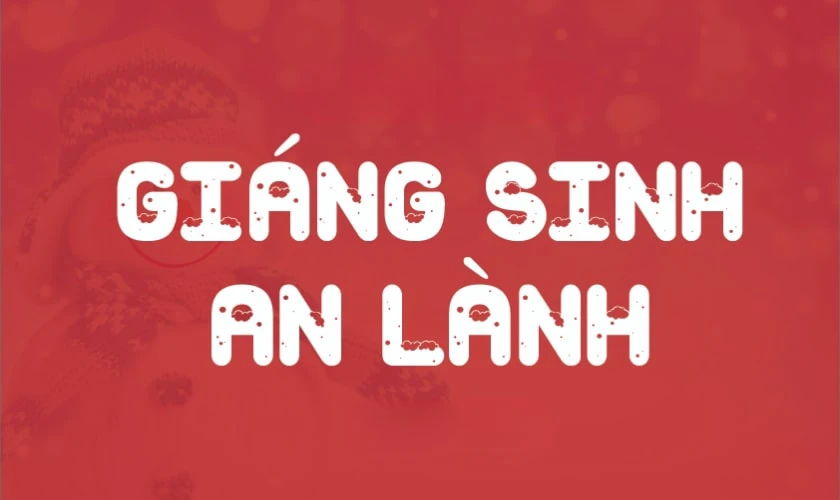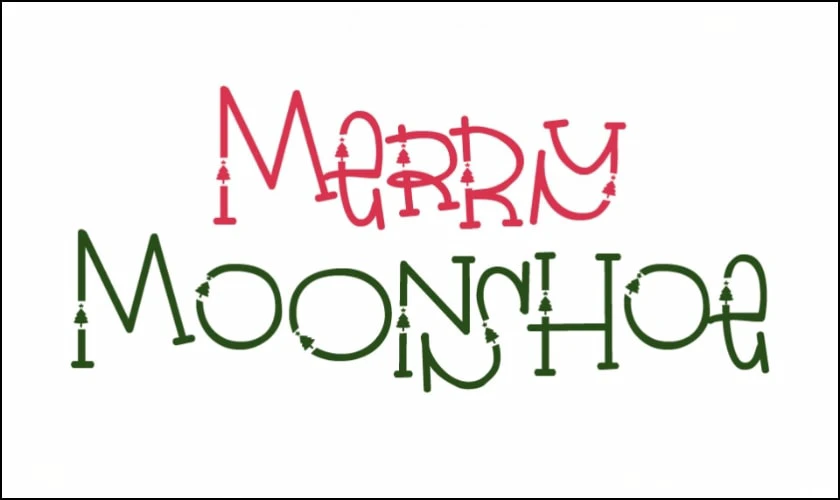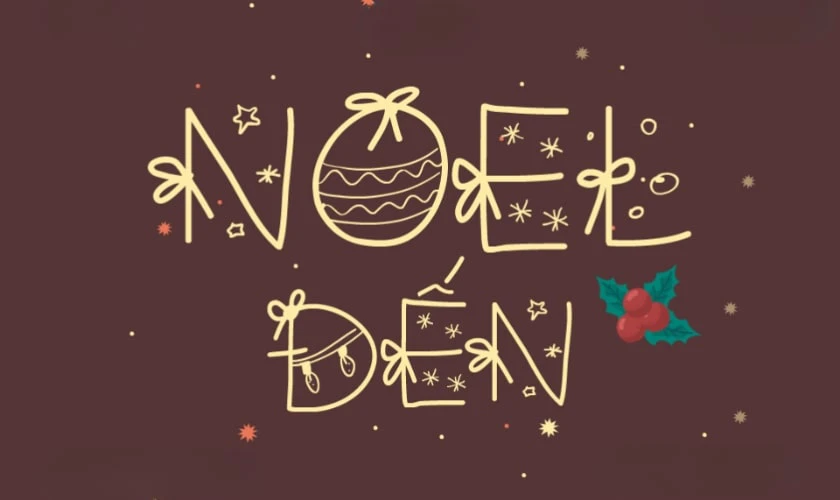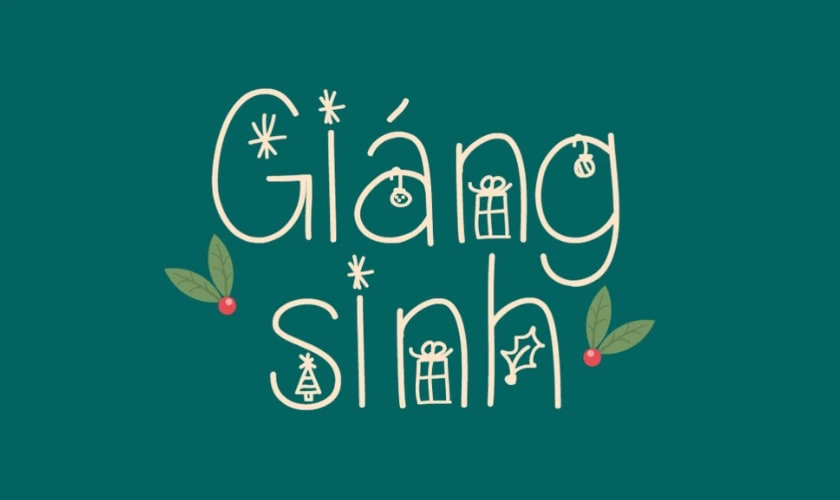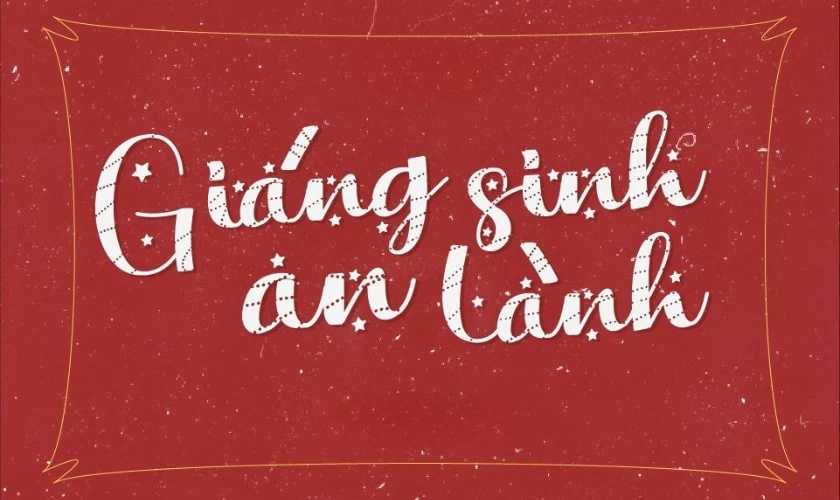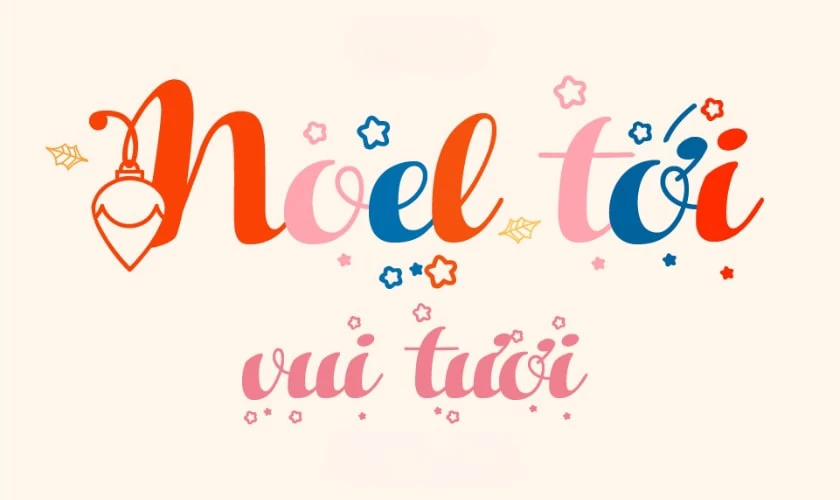
75+ font chữ Giáng sinh đẹp, Font Noel Việt hóa miễn phí
Font chữ Giáng sinh luôn là yếu tố quan trọng trong các thiết kế Noel cuối năm. Bộ sưu tập font Noel Việt hóa giúp người dùng dễ áp dụng cho thiệp, banner, poster. Các font chữ được chọn lọc kỹ, dễ đọc và phù hợp nhiều phong cách. Khám phá ngay danh sách font miễn phí dưới đây để hoàn thiện thiết kế Giáng sinh nhanh hơn.
Bên dưới đây là 8 font chữ Giáng sinh phổ biến, được sử dụng nhiều nhất.
Mẫu chữ đơn giản nhưng vẫn mang một vẻ đẹp ấn tượng. Giúp bạn trang trí chiếc thiệp Giáng sinh cho bạn bè, người thân thật ý nghĩa.
Font chữ Germania One được lấy ý tưởng từ kiểu chữ Đức. Với thiết kế cách điệu ấn tượng, Germania One sẽ mang lại không khí vui vẻ cho đêm Giáng sinh.
Nếu bạn đang tìm kiếm sự độc đáo và mới lạ thì đừng bỏ qua font chữ Christmas Lights.
Mẫu phông chữ Giáng sinh - Christmas Lights sẽ mang đến một bữa tiệc “sáng bừng”.
Mang một vẻ ngoài cổ điển và truyền thống, Sacred Bridge mang nét vẽ sắc sảo. Tạo nên những nét chữ hoàn hảo, giúp bạn trang trí những chiếc thiệp đầy màu sắc.
Mang những đường nét đậm táo bạo, mẫu chữ Comfy Christmas rất phù hợp cho dịp Giáng sinh.
Arima là một phông chữ Giáng sinh do NDISCOVER thiết kế. Mẫu chữ dễ đọc với nét chữ thư pháp uốn cong nhẹ nhàng. Nhờ đó là giúp tạo nên một buổi tiệc đầm ấm khi dùng mẫu chữ này để trang trí.
Mẫu chữ Giáng sinh mặc dù có vẻ đơn giản nhưng vẫn mang đến vẻ đẹp sinh động, cuốn hút. Dù để trang trí bữa tiệc hay viết thiệp đều phù hợp đó.
Pinyon Script là mẫu chữ có nét cong, uốn lượn kết hợp cùng đường nét góc cạnh. Tạo nên dáng chữ vừa mềm mại vừa mạnh mẽ. Đây cũng là gợi ý hoàn hảo cho đêm Giáng sinh đấy.
Font chữ Giáng sinh Việt hóa miễn phí luôn là yếu tố quan trọng giúp thiết kế mùa lễ hội của bạn trở nên ấn tượng và thu hút hơn. Việc chọn đúng font không chỉ truyền tải không khí ấm áp mà còn đảm bảo tính thẩm mỹ. Nội dung sau sẽ tổng hợp những font chữ đẹp và ấn tượng để bạn có thể tải về ngay:
Mountains of Christmas là font chữ giáng sinh được dùng rất phổ biến hiện nay. Font có nét bo tròn, dày và tạo cảm giác vui nhộn. Kiểu chữ này phù hợp thiết kế thiệp Noel và banner sự kiện. Font hỗ trợ đầy đủ tiếng Việt nhờ bảng Latin Extended.
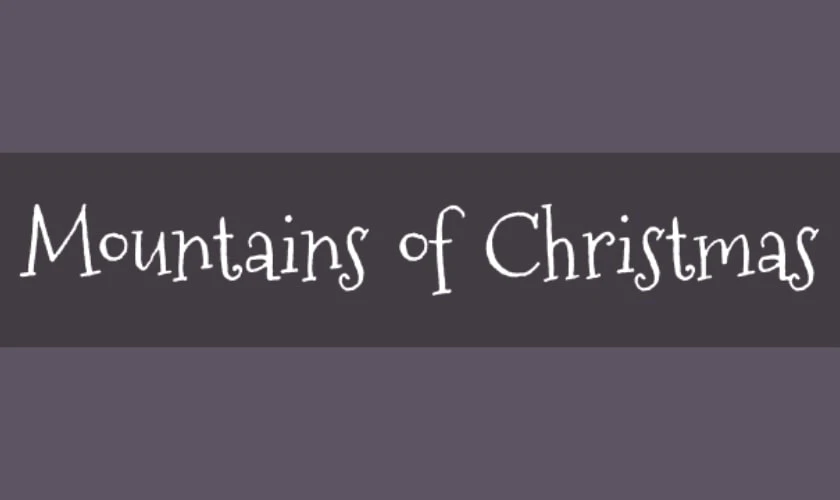
Người dùng có thể áp dụng font cho tiêu đề và nội dung ngắn. Font chữ giáng sinh này giúp thiết kế trở nên ấm áp và gần gũi. Với cách sử dụng rất đơn giản và dễ cài đặt. font phù hợp cho cả người mới bắt đầu thiết kế.
Coiny là font chữ giáng sinh mang phong cách tròn và đậm. Font tạo cảm giác vui tươi và nổi bật trên nền sáng. Kiểu chữ này phù hợp làm tiêu đề Noel hoặc poster trang trí. Font hỗ trợ tiếng Việt đầy đủ và hiển thị rõ nét.
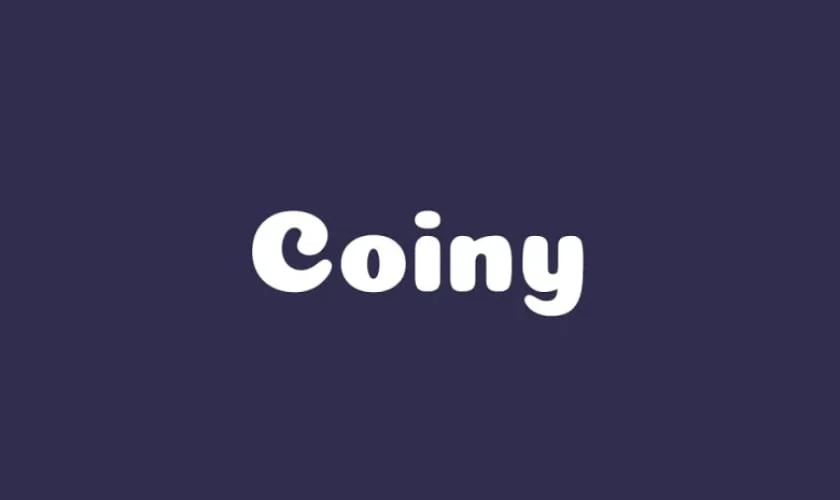
Người dùng có thể dùng font cho banner trường học hoặc báo tường Noel. Font chữ giáng sinh Coiny giúp nội dung dễ đọc và thu hút. Do đó, font chữ này phù hợp nhiều độ tuổi người xem.
Font 1FTV VIP Starry Fayez mang phong cách chữ phát sáng độc đáo. Font chữ giáng sinh này tạo hiệu ứng lung linh như đèn Noel. Kiểu chữ phù hợp cho thiết kế ban đêm và background tối. Font đã được Việt hóa đầy đủ và dễ sử dụng.
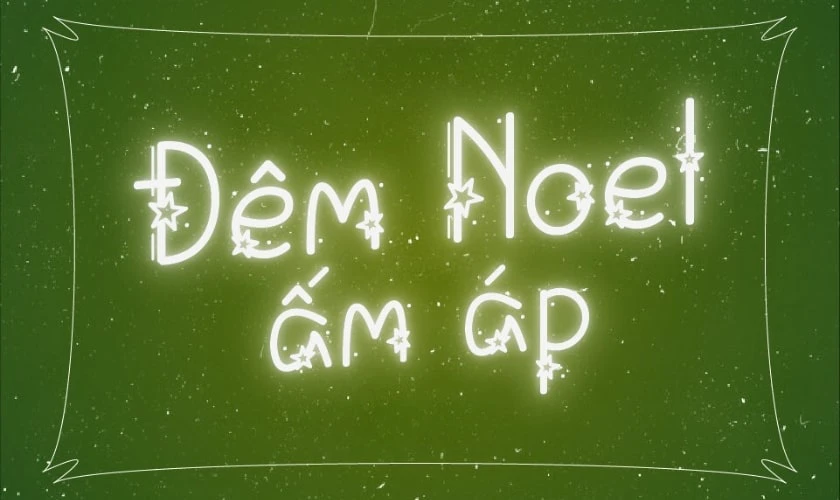
Khi dùng font, nội dung trở nên nổi bật hơn. Font phù hợp cho thiệp Noel kỹ thuật số. Người mới có thể dùng font cho Canva hoặc Photoshop. Đây là lựa chọn tốt cho thiết kế sáng tạo.
Font 1FTV Christmas Dream có nét chữ mềm và tròn như những chiếc tất. Font chữ giáng sinh này mang cảm giác ấm áp và gần gũi. Font phù hợp để làm thiệp gia đình và lời chúc Noel. Chữ hiển thị rõ khi in ấn hoặc đăng mạng xã hội.
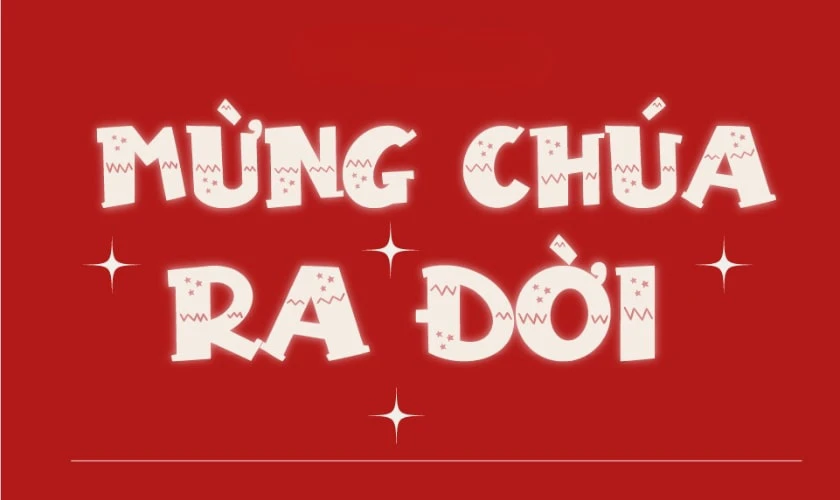
Đặc biệt, font đã được Việt hóa chuẩn dấu. Người mới học thiết kế có thể dùng nhanh. Font kết hợp tốt với hình minh họa Noel. Đây là font được nhiều người dùng dịp cuối năm.